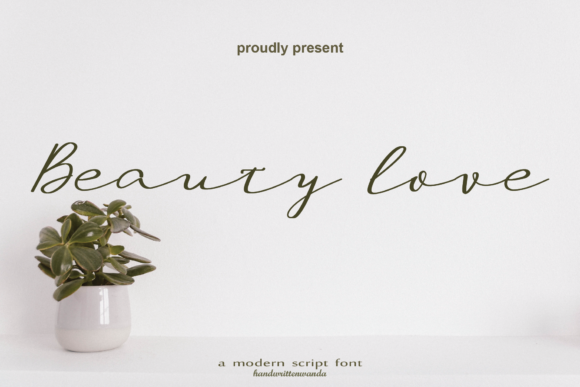
Beauty Love
Beauty Loveのような高品質の素材をお探しの場合、このプレミアムパッケージはクリエイティブなプロジェクトに素晴らしい選択です。
POD(オンデマンド印刷)製品、結婚式の招待状、またはソーシャルメディアのグラフィックを作成している場合でも、Beauty Loveは理想的です。